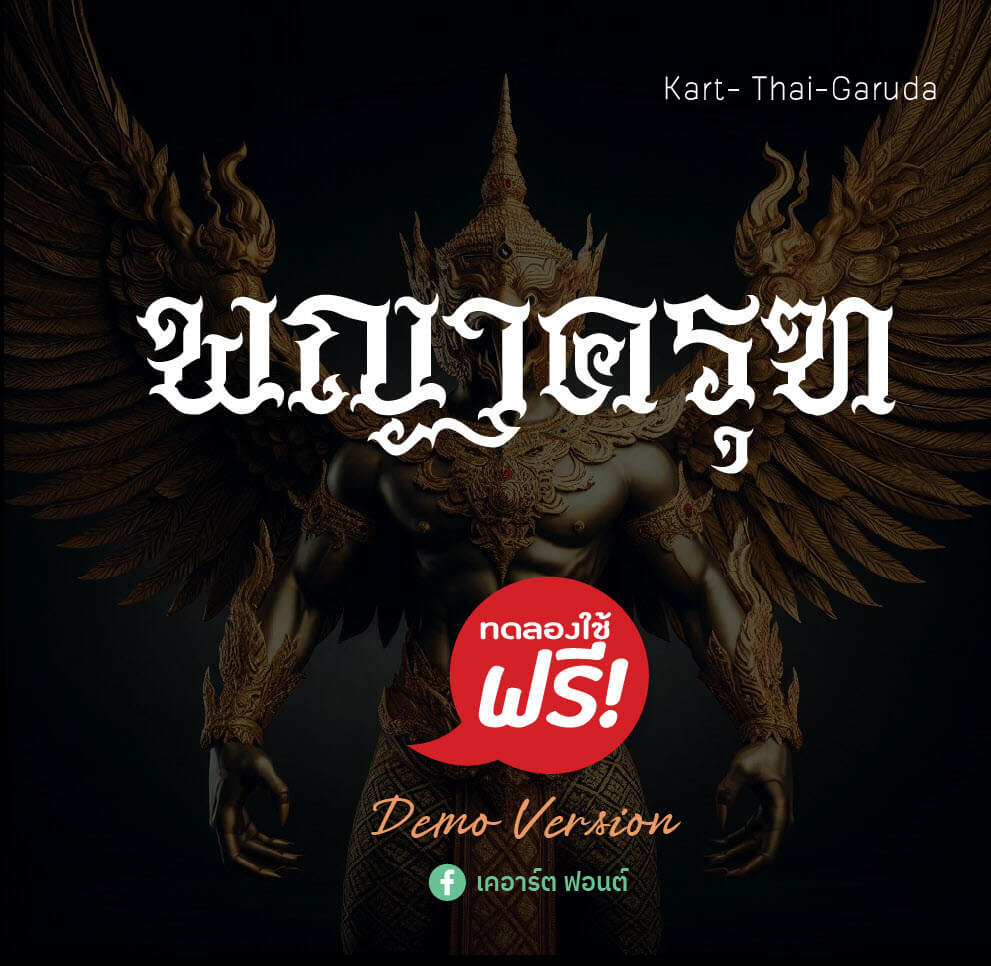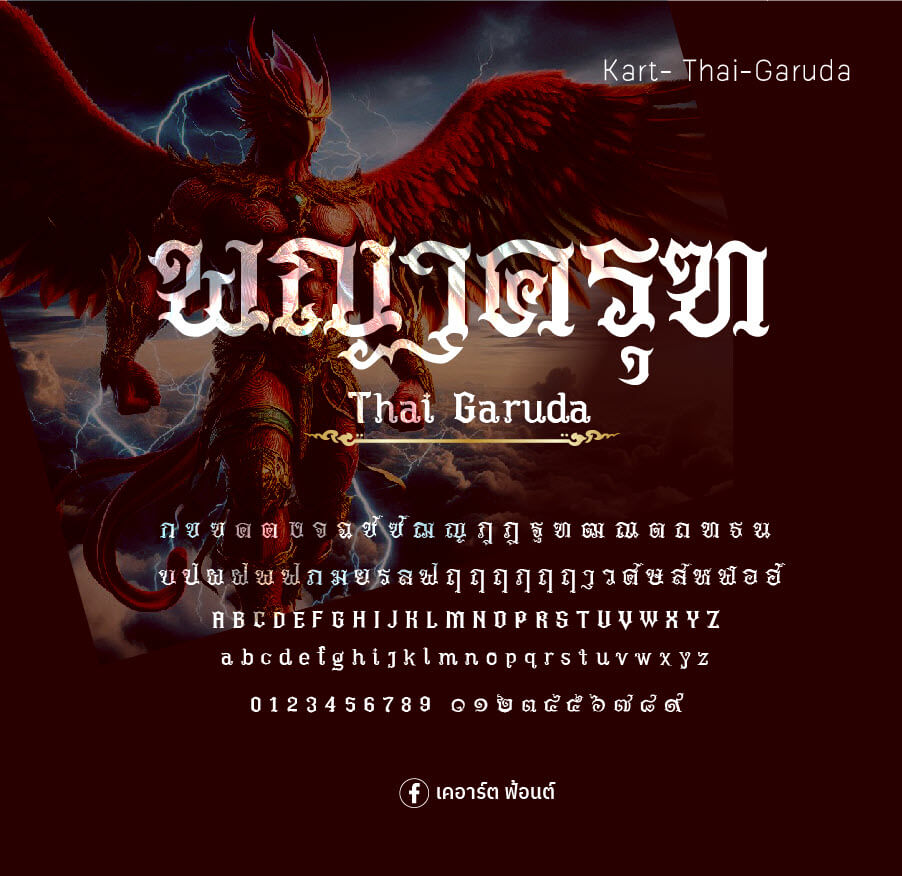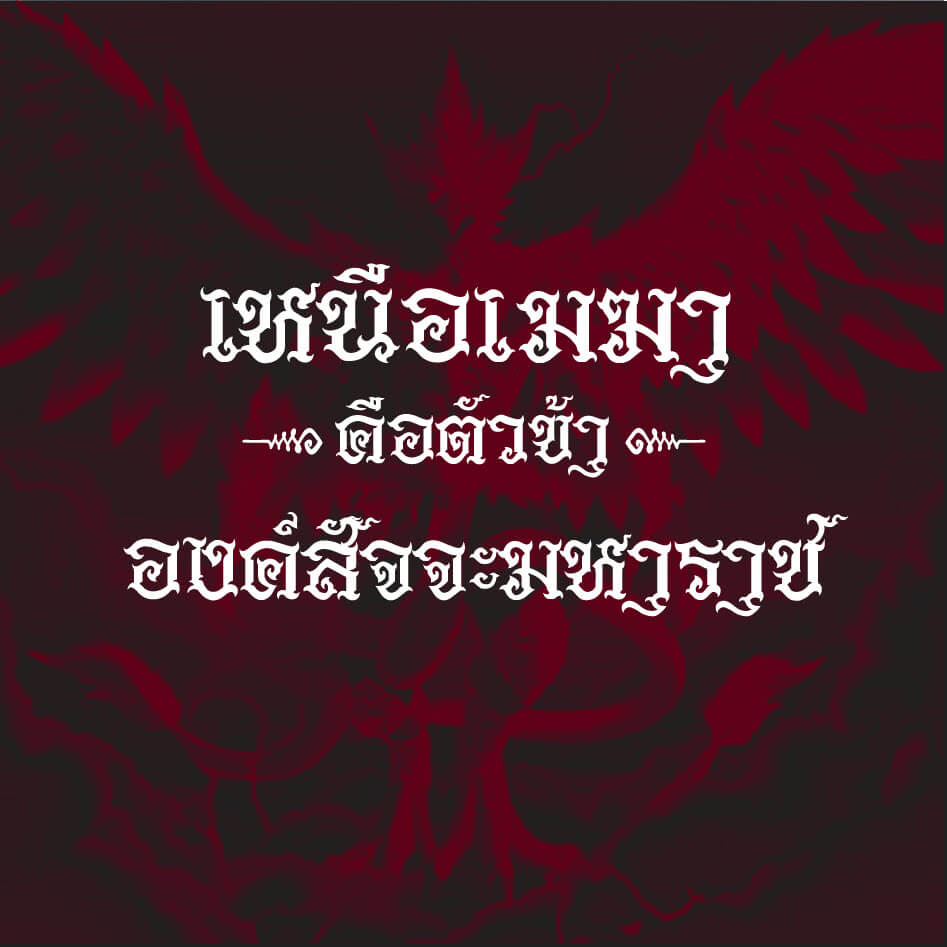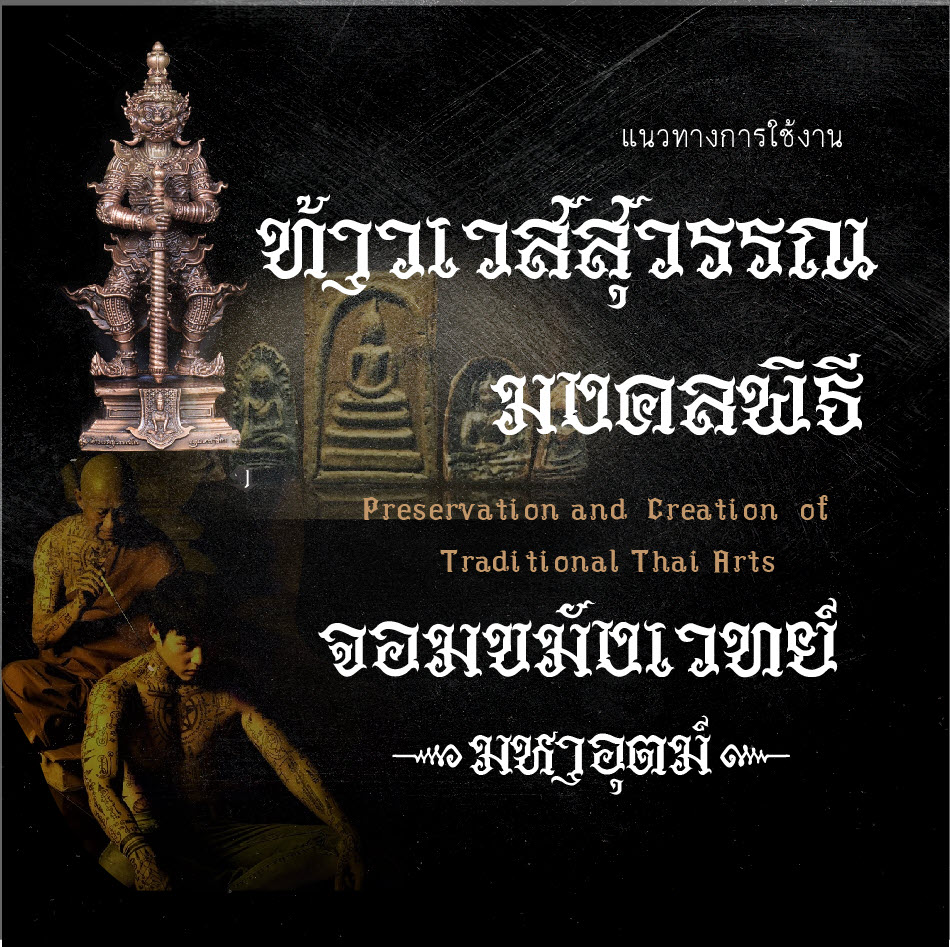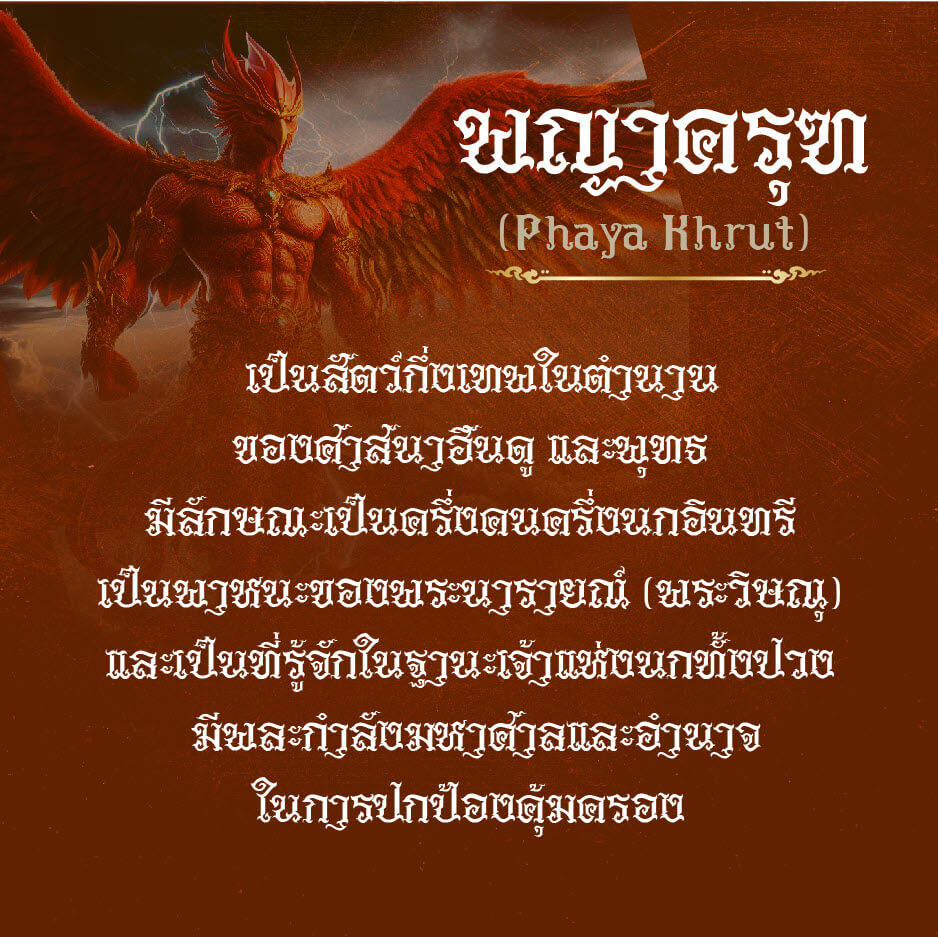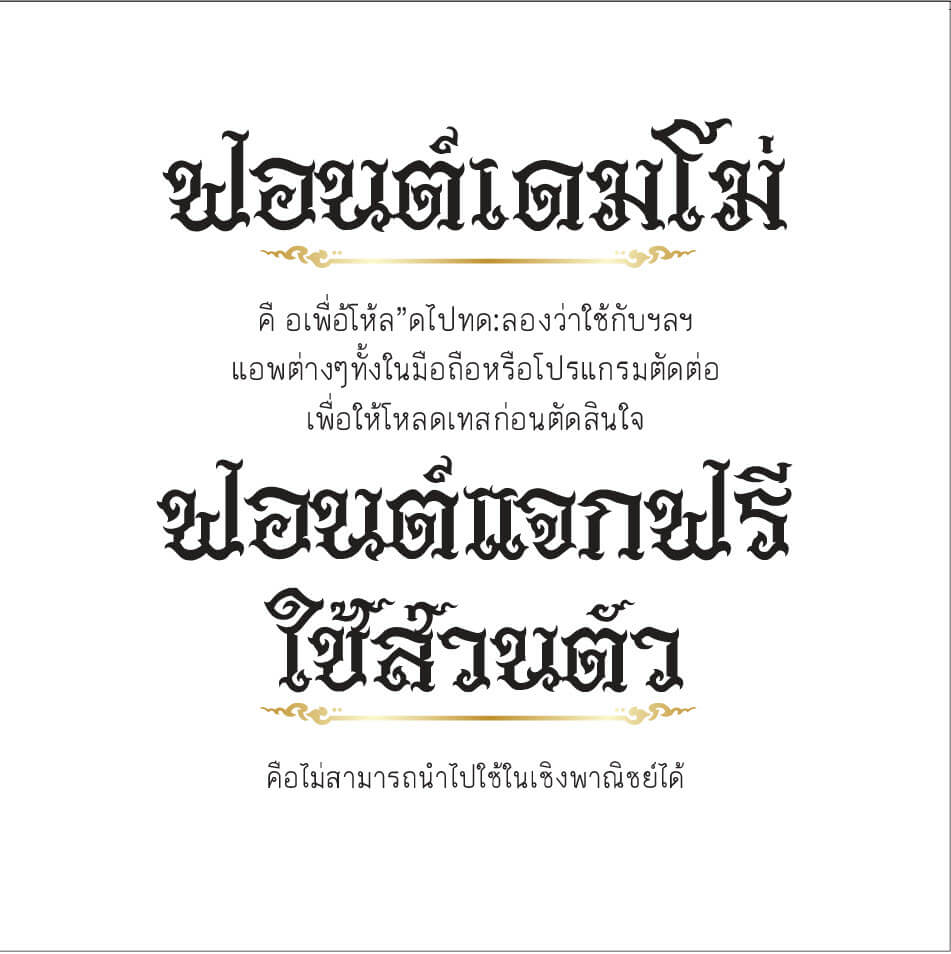
เคอาร์ต พญาครุฑ – เป็นฟอนต์ที่แนวคิดความแหลมคม ของกงเล็บและจงอยปากพญาครุฑ ฟอนต์จึงออกมาแหมคมดุดัน และสง่างามเหมือนกางปีก
เคอาร์ต พญาครุฑ (Kart-Thai-Garuda)